美术字体是一种新型装饰中具有代表的意义的艺术字体,经过加工、美化、装饰而成的文字,是一种运用装饰手法美化文字的一种书写艺术,是艺术加工的实用字体。字体特征整齐、醒目、美观、易于识别字体。是开展宣传、教育不可缺少的工具,如横幅标语、黑板报、墙报、会场布置、展览会,以及商品包装和装潢,各类广告、报刊杂志和书籍的装帖上等都离不开美术字。
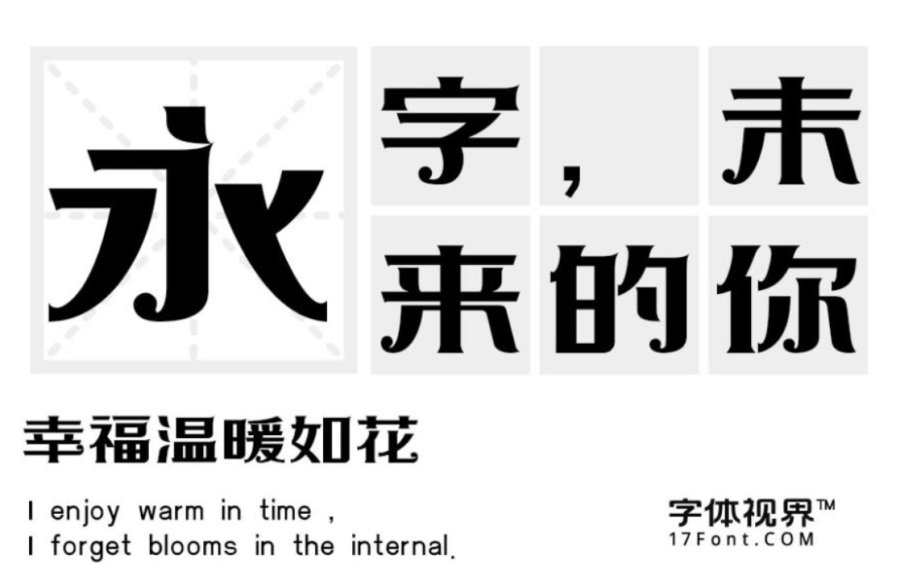
上首车车体:这款字体风格稳重呈方块形,字体笔画竖折处细节处理,是此套字库的亮点。字体传达出一种生活态度、一种独到风格,典雅大方、挺拔秀丽,以形态美突出语言内在涵义。整体特征坚硬、有力,具有现代、国际化的指向性,适用于搭配标志、广告标语、商业广告等高端属性。
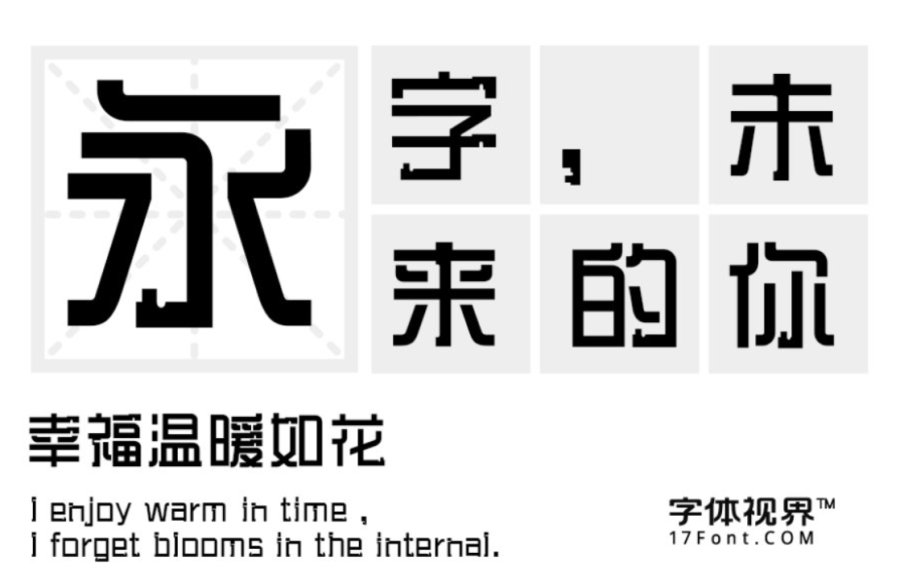
三极吴哥简体:这是一款装饰意味浓厚的美术字体。这款字弱化了笔画中大部分的弧线,笔画的右方统一做了圆角处理,将横、竖和勾设计别样的圆口留白,另外勾增加了方块的小设计,大胆创造,又不失文字的识别性。字形稳定坚实,适用于品牌广告、产品包装设计和建筑行业应用。
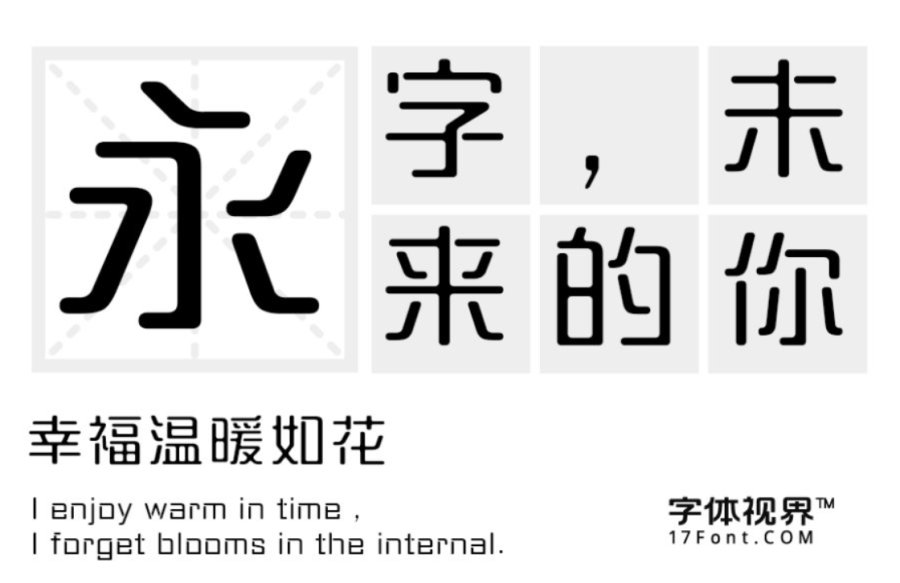
三极瑚琏简体:这款字体最大的特征是笔画交叉处的内侧添加了圆角,不同状态的连续弧线,彼此相融,打破常规不拘一格。风格朦胧柔美,让人感觉轻松休闲,不失美观大方。适用于品牌广告和产品包装的设计。